什么字体才是设计师最爱的使用率高的?它们都有什么显著特点?其实千人千面,每个设计师都有自己不同的喜好,不过阅读舒适易于字体识别,方正得体、浑然天成并且具有个性特色的字体一定是所有人都喜欢的。一张设计精美的小小名片可以玩转品牌,使用大胆的图片色彩、独特的形状字体可以表现品牌的创造力、艺术性和趣味。
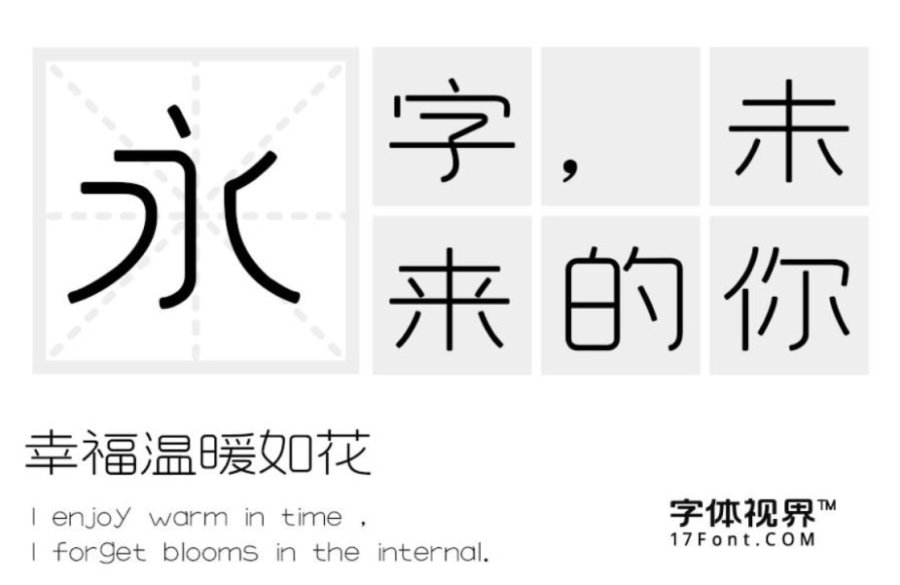
这款“上首秀圆体”字体风格清新秀丽,笔画瘦长,转角圆润,整体特征柔和、圆润,具有现代感十足,作为名片字体最为合适不过了,字形清晰。无衬线字体的特征更具有现代感。还适用于搭配标志、广告标语、商业广告等高端属性。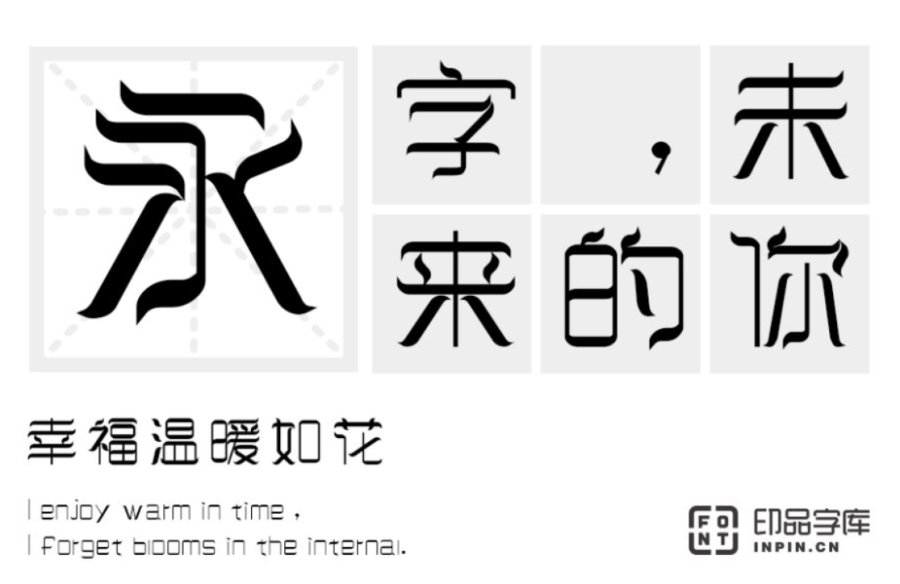
这是一款自带美颜效果的字体。从横撇点勾处做了仿丝带设计,字里行间不再肉,细节处醒目突出,让字体自带飘逸飞扬的自由感,字形正如其名“印品飘艺体”。给人一种简约的美感,满满的艺术气息。作为名片字体不仅简约大方,还传达出个人个性魅力。还适用于封面设计、广告设计、影视以及社交网络的个性化用字等。
这些字体的最大特征就是风格中性,基本可以满足大多数文本的属性,也很稳定。中性不代表它们没有个性,恰恰相反,它们可根据内容的语境,通过版面设计,塑造出不同的阅读个性,赶快搜字体了解更多字体信息吧。